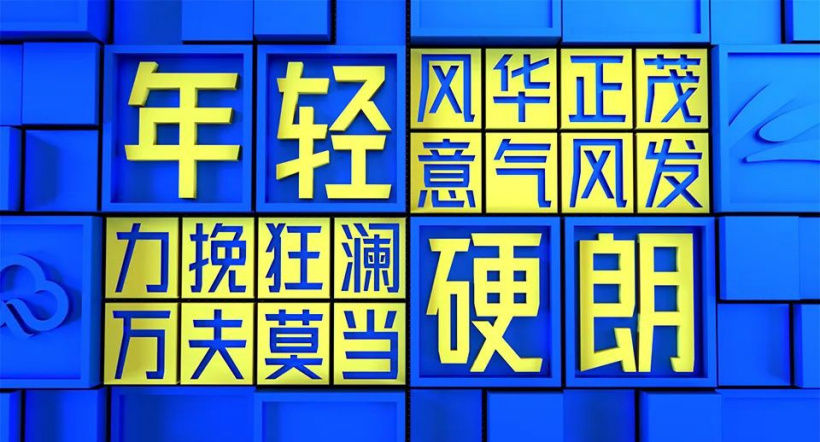
IT之家 9 月 16 日消息,今日,金山云发布了首款免费商用字体“金山云技术体”。据介绍,这款字体历时四年积累完成且永久免费,在印刷品上和显示屏上能够创造出令人舒适的阅读体验。
官方说明显示,金山云技术体是一款无衬线体,提供一种标准版字重,文字参照 GB2312 简体中文编码字符标准。包含国标一级、二级字库汉字 6763 个,外文及数字符号 795 个,字库总字符数 7558 个。
设计方面,金山云技术体整体造型设计风格偏向年轻、硬朗、具有活力,重新定义 1:0.84 的字宽比例,设计了整体、左右、上下等搭配方法。同时,字体的笔画设计根据整字权重划分粗细进行搭配,在笔画的衔接和末端处使用了 12 度的倾斜设计。